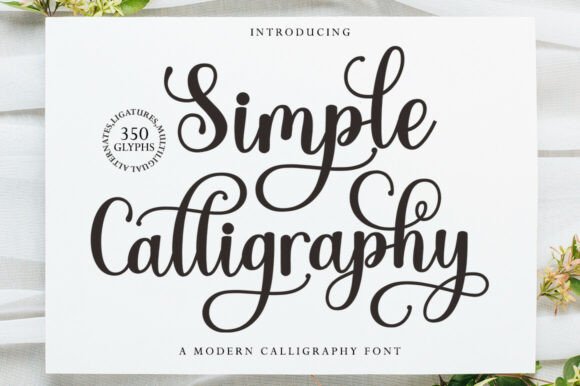
Simple Calligraphy
Trovare i giusti elementi di design può essere difficile, ma Simple Calligraphy offre una collezione eccezionale che eleva istantaneamente il tuo lavoro.
Che tu stia creando prodotti POD (Print on Demand), partecipazioni di nozze o grafiche per i social media, Simple Calligraphy è la scelta ideale.